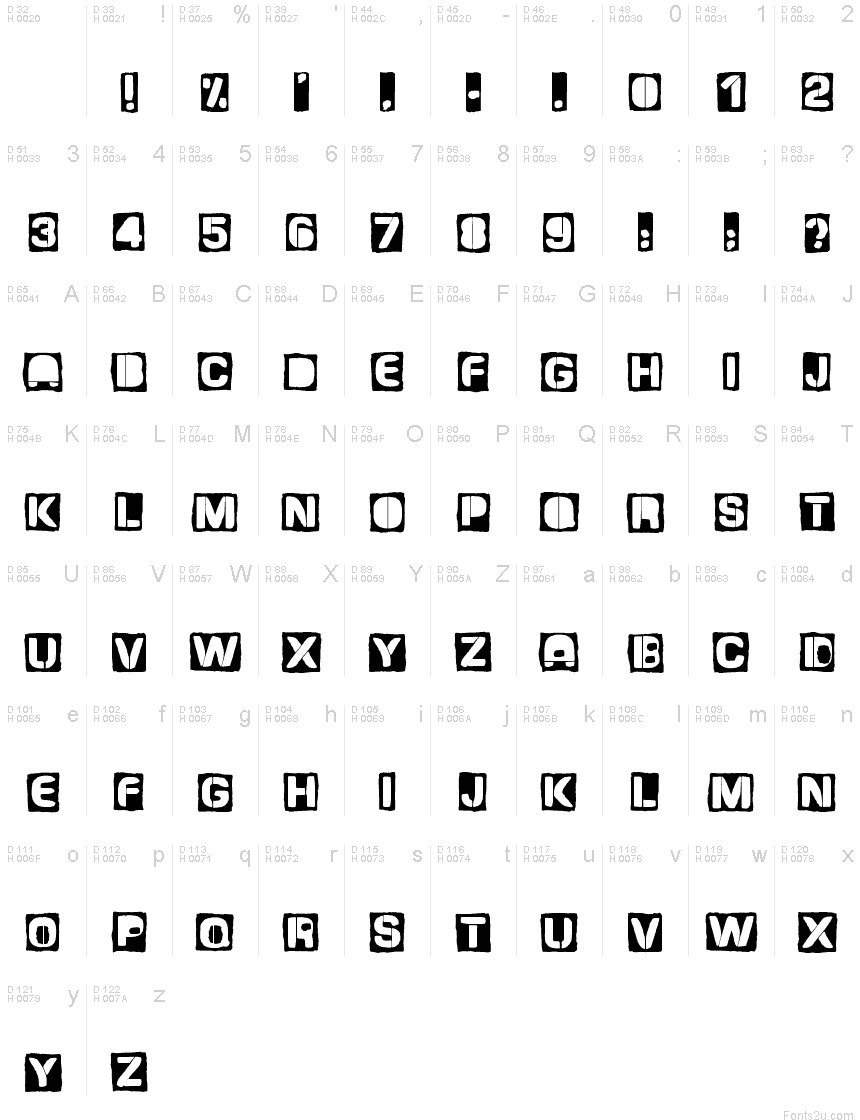
Krój pisma Arthur autorstwa Falka Lehmanna >AKUT< to darmowy, dekoracyjny font o odważnym, blokowym charakterze, który wygląda, jakby wprost zeskoczył z oklejonej naklejkami rampy skejtowej. Każda litera mieści się w nieregularnym, „wytatuowanym” atramentem kwadracie, niczym ręcznie wycięta pieczątka na papierze, z miękkimi, zaokrąglonymi wnętrzami napierającymi na szorstkie, masywne krawędzie. Efekt jest wyrazisty, ale zabawny – bardziej przypomina mural w stylu street-art niż nudny nagłówek – i nadaje tekstom gęstą, wyczuwalną formę, która wręcz pulsuje energią DIY.
Jako darmowy font, Arthur świetnie sprawdza się na plakatach koncertowych, w zinach, brandingu odzieży streetwearowej, grafikach na imprezy dla dzieci, tytułach gier i zestawach naklejek. Zwarta, pudełkowa rytmika trzyma się kupy nawet w najbardziej chaotycznych układach, więc możesz układać słowa w stosy, nakładać je na siebie czy obracać bez utraty czytelności. Aby zachować równowagę, połącz Arthura z czystym krojem bezszeryfowym w tekście głównym, a Arthurowi powierz duże, „krzykliwe” elementy.
Arthur